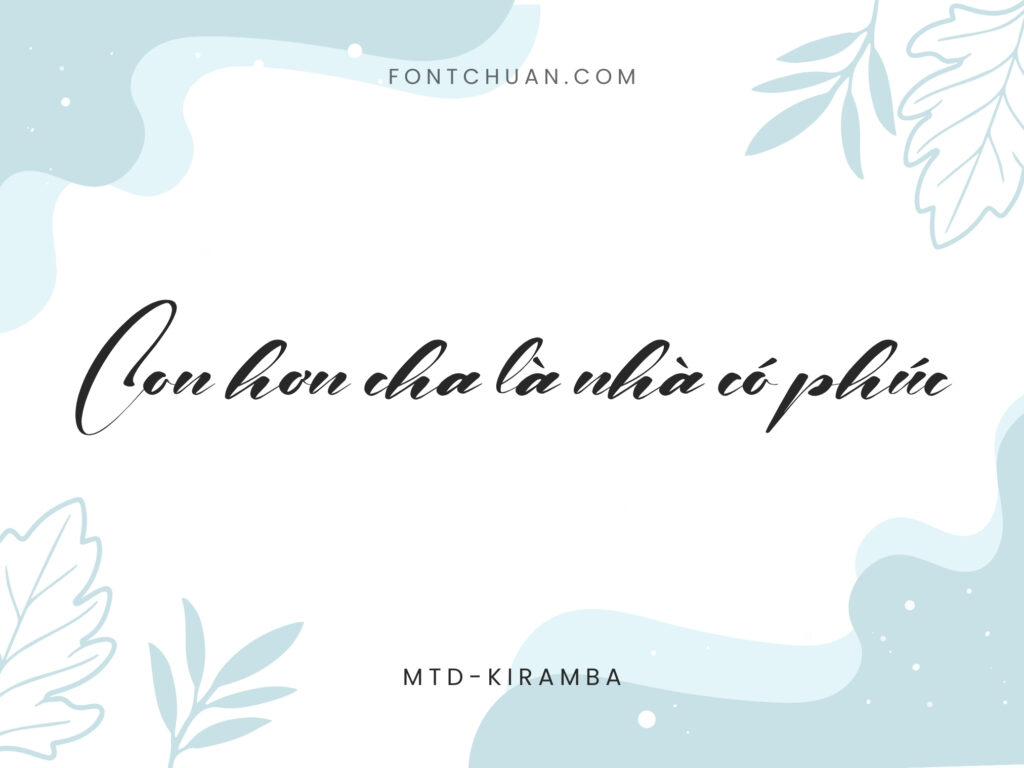
Font MTD Kiramba Việt Hóa
Font MTD Kiramba là một phông chữ viết tay mang phong cách thư pháp hiện đại, được thiết kế với các nét chữ mềm mại và uyển chuyển, tạo cảm giác tự nhiên và thanh lịch. Font đã được Việt hóa bởi Mộc Hạ, hỗ trợ đầy đủ tiếng Việt cùng hơn 90 ngôn ngữ khác, mở rộng khả năng ứng dụng trong các thiết kế đa ngôn ngữ. Đây là một trong những phông chữ được cộng đồng thiết kế đánh giá cao và sử dụng trong nhiều dự án sáng tạo, đáp ứng nhu cầu đa dạng của người dùng.
MTD Kiramba nổi bật với phong cách viết tay tự nhiên và thanh lịch, mang đến cảm giác thân thiện và gần gũi. Font rất phù hợp cho các thiết kế logo, tiêu đề, bao bì sản phẩm, thiệp mời và các ấn phẩm đòi hỏi sự sáng tạo và cá nhân hóa. Các ngành nghề phù hợp bao gồm quảng cáo, giáo dục, công nghệ, thiệp cưới và ảnh cưới. Font này cũng lý tưởng cho các sự kiện như Tết, Giáng sinh, Valentine và các lễ hội khác.